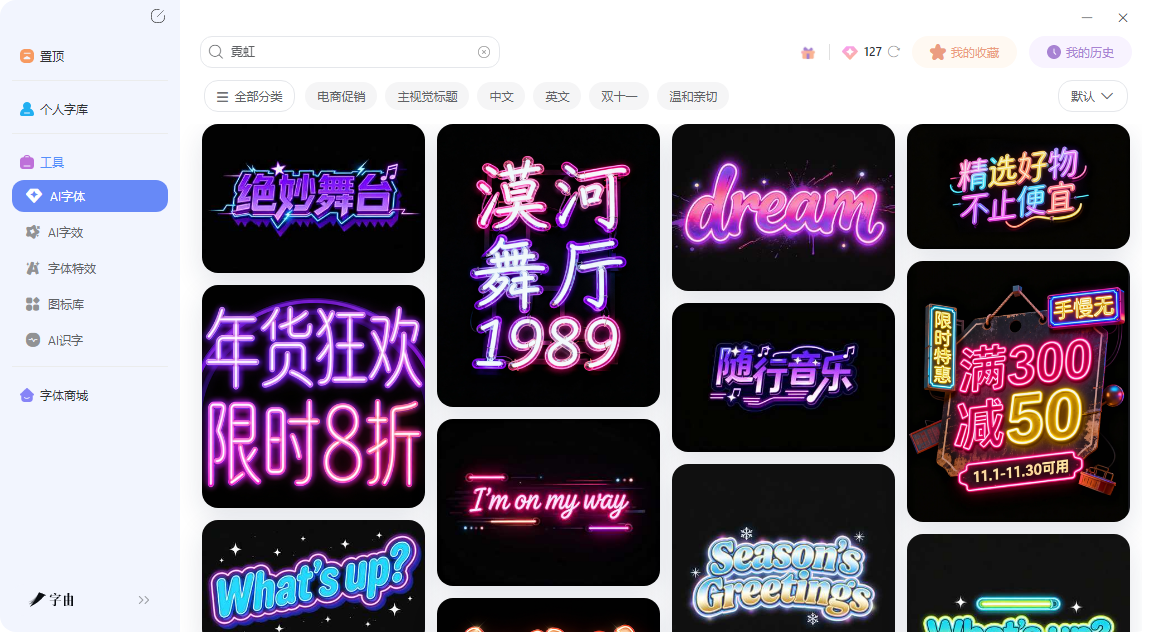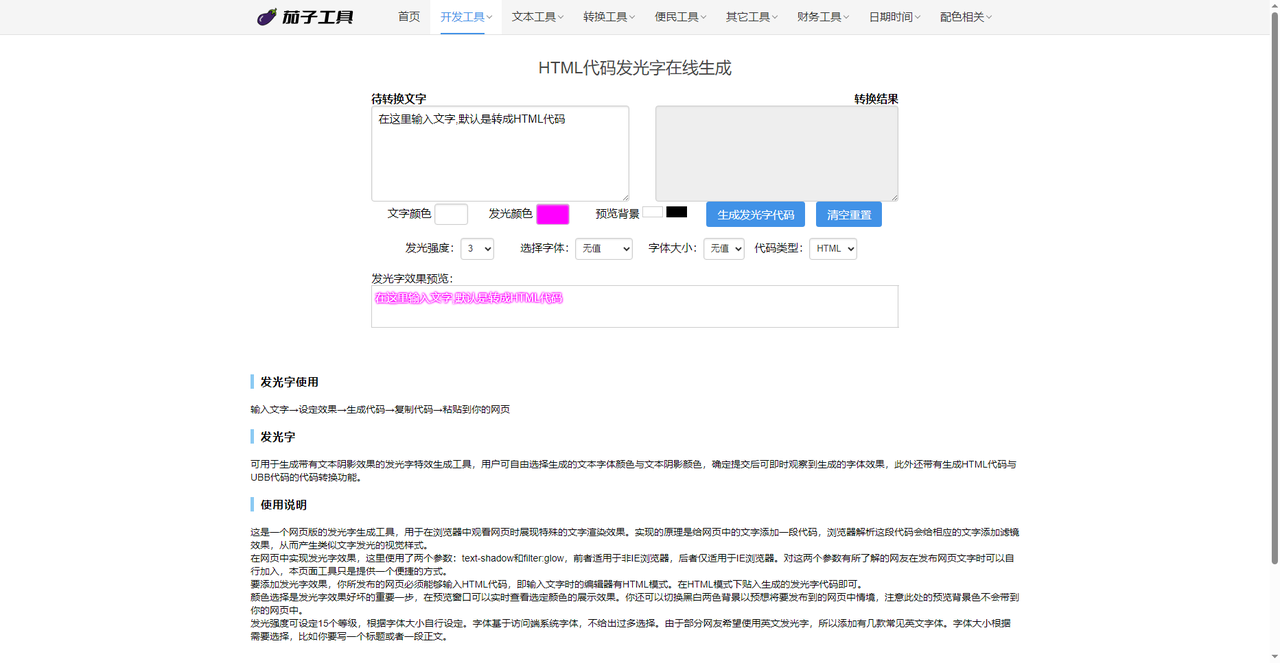
荧光字在线制作不用愁,霓虹模板专业生成器一键get
你有没有注意过,夜市大排档的招牌、酒吧门口的霓虹灯、派对的邀请函标题,为什么总是那么吸睛?因为荧光字。那种自带发光、色彩鲜艳的视觉效果,在暗光环境下特别抓人。以前想做荧光字,得打开PS,选中文字图层,加外发光、内发光、调整混合模式、改颜色、调大小……参数稍微不对,效果就假。现在不用这么麻烦了,网上有不少荧光字在线制作工具,输入文字选个模板,几秒钟就能出效果。今天实测了5 款荧光字制作工具,从AI一键生成到网页代码,从静态图到动态闪字,覆盖了不同场景的需求。
先聊字由,很多人知道字由是字体管理工具,但它的AI字体功能里,藏着一个专门的“霓虹灯”分类——那就是做荧光字的捷径。为什么字由适合做荧光字?因为荧光字的核心是“发光”。普通字体没有光效,你得自己加。但在字由的AI字体模板库里,有几十款专门做发光效果的模板:霓虹灯管效果、赛博朋克发光、彩色流光、冷光暖光……每款都是专业设计师调好参数的成品。
打开字由客户端,进入“AI工具”下的“AI字体”,左侧筛选栏里找到“霓虹灯”或“科技感”分类。你会看到一排排自带发光特效的模板预览图——有的像真实霓虹灯管弯曲盘绕,有的像电子屏幕的像素发光,有的像激光镭射效果。
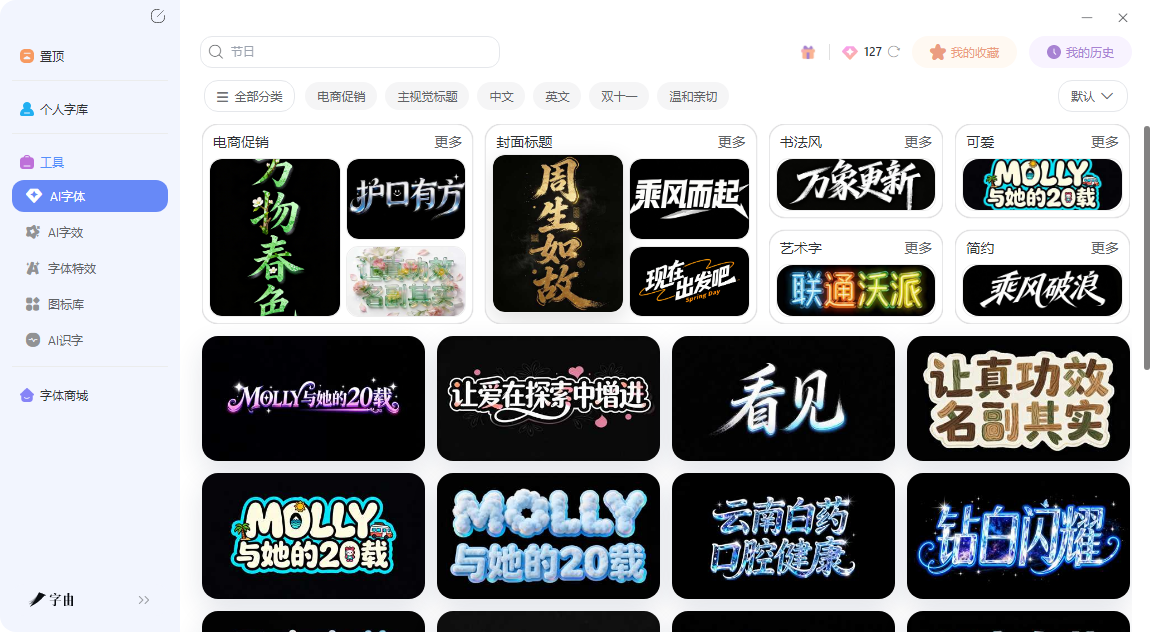
生成后的图片是透明背景的PNG,直接拖进海报里,放在深色背景上,发光效果特别明显。你还可以调整文字的大小和位置,虽然不能像PS那样逐像素修改,但基本的缩放和对齐都支持。
不只是霓虹灯,还有其他发光效果
除了霓虹灯管,字里还有“金属质感”分类下的某些模板也带有高光反射效果,适合做高端品牌广告;“国潮风”里有些烫金发光效果,适合做中式庆典;“科技感”里有赛博朋克风格的蓝色冷光。总共400多种模板,只要跟“光”沾边的,都能翻到合适的。
如果你是夜市摊主、小店主,需要自己做一张促销海报挂门口,字由选个霓虹灯模板改几个字就行,不用再花钱找设计师。如果你是酒吧、Livehouse的活动策划,每周都要换活动海报,字由的霓虹灯模板能帮你快速出图。
2、茄子工具
第二个工具是茄子工具。它不是一个图片生成器,而是一个HTML/CSS发光字代码生成器。也就是说,它生成的不是图片,而是一段网页代码。把这段代码粘贴到你的网站或博客的HTML编辑器里,浏览器打开后,文字就会自动带上发光效果。怎么用?在页面上方输入框里打字,比如“欢迎光临”。然后设置“文字颜色”和“发光颜色”——这是决定发光效果的关键。你可以选红色文字配黄色发光,或者蓝色文字配白色发光。还可以调节“发光强度”(1到15级),强度越高,光晕范围越大。选择“代码类型”为HTML,点击“生成发光字代码”,下面会出现一段代码。复制代码,粘贴到你的网页编辑器(如WordPress、微信公众号后台的HTML模式),保存后文字就会发光。
这个工具适合做网站标题、博客公告、网页横幅。比如你有一个个人网站,想让首页的“作品集”三个字发光,用茄子工具生成代码贴进去就行。不需要懂CSS,不用写代码。而且生成的发光字在手机和电脑上都能正常显示,因为它是标准的CSS text-shadow属性实现的。
3、发光文本生成器
第三个工具是发光文本生成器(截图显示为curved-text相关工具)。这个工具比茄子工具更高级,它不仅支持发光特效,还支持文字弯曲——你可以把文字排成弧形、圆形、波浪形,同时加上发光效果。操作界面里可以上传背景图片或选择透明背景,添加文本,选择字体(Arial、Georgia、Courier New等),设置字体大小,打开“发光”效果,调节发光颜色(RGB滑块)、发光模糊程度(效果大小)。最特别的是“弯曲任何文本”功能——你可以把原本平直的文字弯曲成弧形,适合做圆形Logo、徽章、印章效果。
预览窗口实时显示效果,满意后点击“下载图片”,生成PNG。这个工具适合做派对邀请函、活动海报、社交媒体封面。比如你要做一个生日派对的电子邀请函,标题“Happy Birthday”弯成弧形,加上粉色发光,比普通排版有氛围得多。
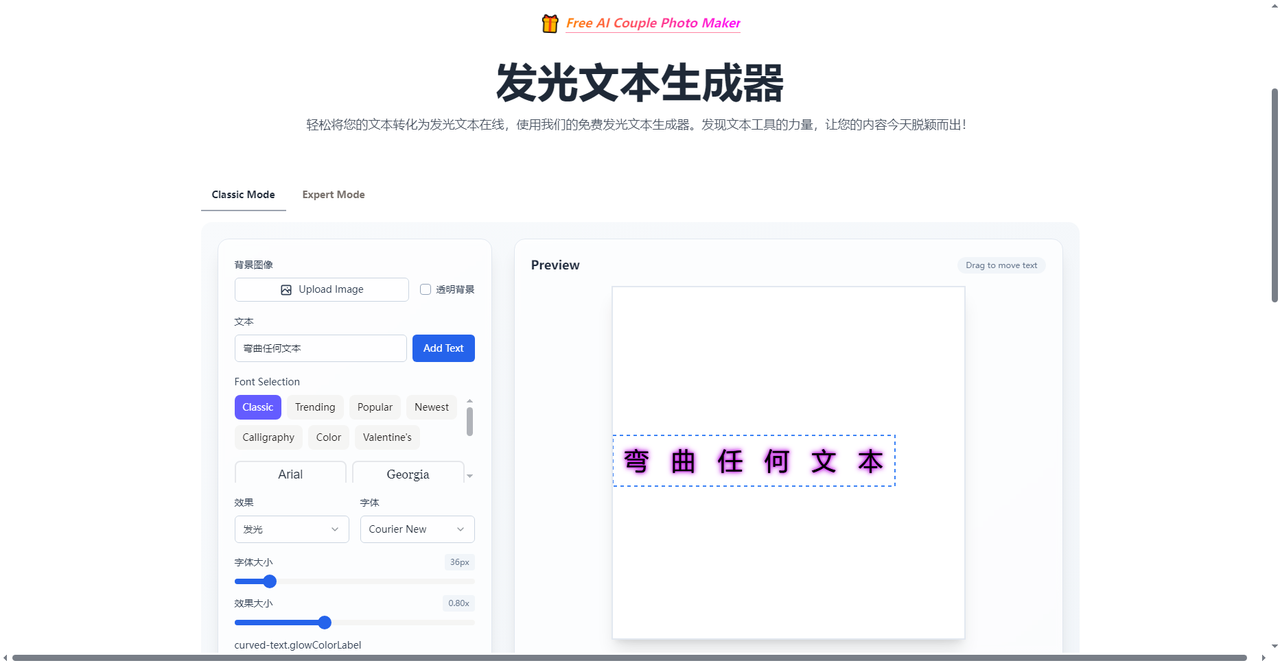
4、千千秀字
第四个工具是千千秀字。它的功能和茄子工具类似,也是一个网页发光字代码生成器。界面几乎一样:输入文字,选文字颜色、发光颜色、预览背景(黑/白),调发光强度(1-15),选择字体和字体大小,生成HTML代码或UBB代码。千千秀字的说明更详细。它解释了发光原理:非IE浏览器用
text-shadow属性,IE浏览器用filter:glow。这意味着生成的代码兼容性更好,在老旧浏览器上也能显示。它还提示用户:要添加发光字效果,你发布的网页必须能输入HTML代码(比如WordPress、微信公众号后台)。
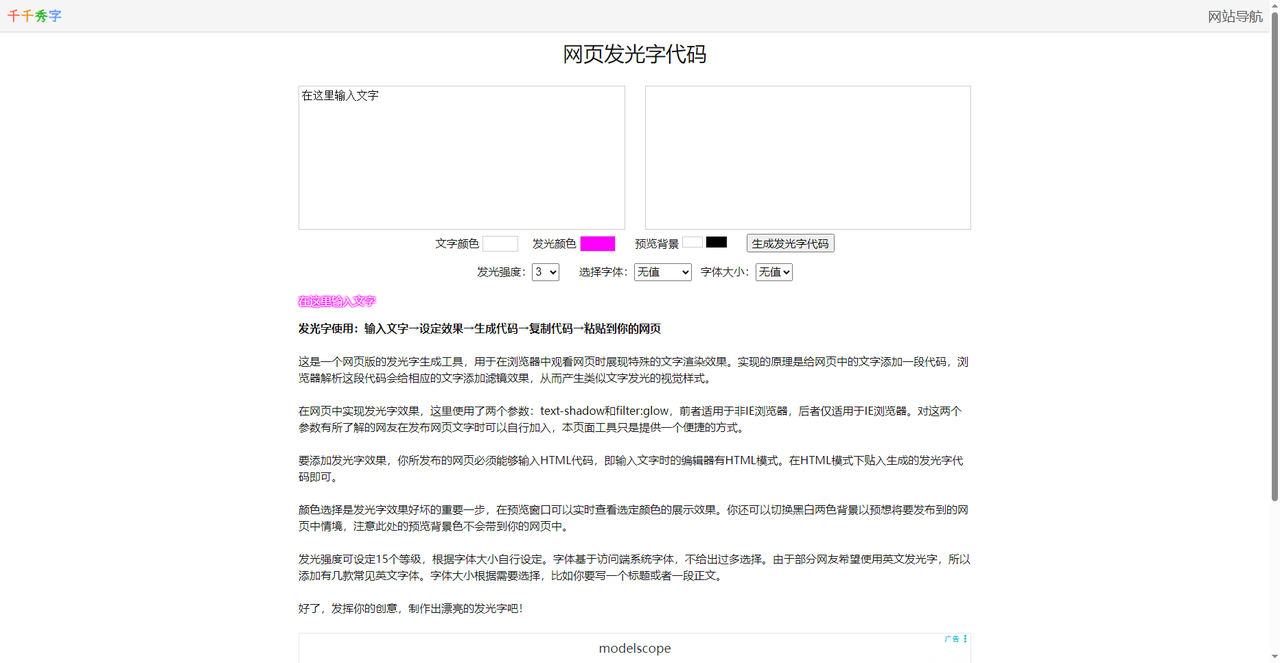
5、急切网
第五个工具是急切网。它和前几个完全不同——它生成的是动态流光闪字,也就是GIF动图。文字会像跑马灯一样流动闪烁,颜色不断变化,非常抢眼。点击“制作流光”,系统会生成一张动态GIF图片,可以直接下载。这种闪字效果在2000年代的非主流QQ空间时期特别流行,现在依然适合做微信表情包、抖音评论区动图、派对邀请函的装饰。比如你想给朋友发一句“生日快乐”的闪字表情,用急切网做一张,比普通文字有趣得多。
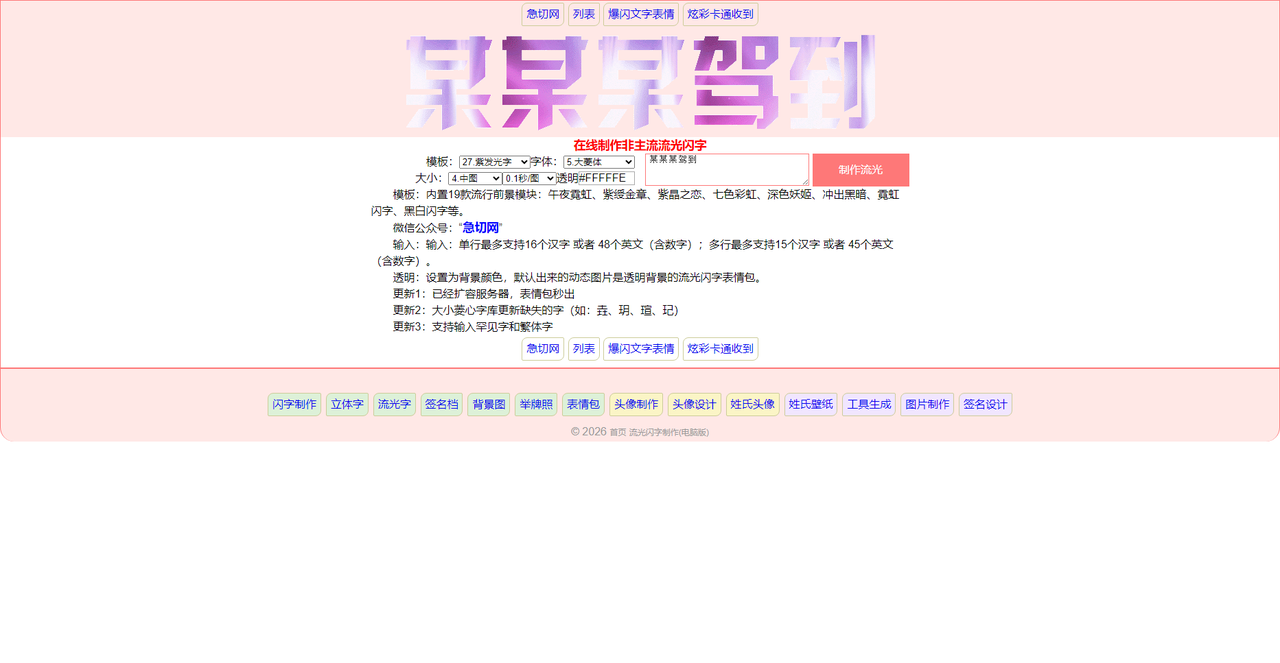
5款荧光字制作工具,定位各有侧重,字由最适合做商业海报、店铺招牌、活动物料的静态荧光字标题,400多种霓虹灯模板10秒出图;茄子工具和千千秀字适合网站开发者给网页文字加发光效果,生成代码粘贴即用;发光文本生成器支持文字弯曲+发光,适合做弧形Logo和邀请函;急切网做动态流光闪字,适合表情包和派对装饰。选哪个,看你要把荧光字用在哪。做印刷海报用字由,做网站标题用茄子工具,做弧形徽章用发光文本生成器,做表情包用急切网。不用纠结,打开网页试一下,输入你的文字,几分钟就能出效果图。